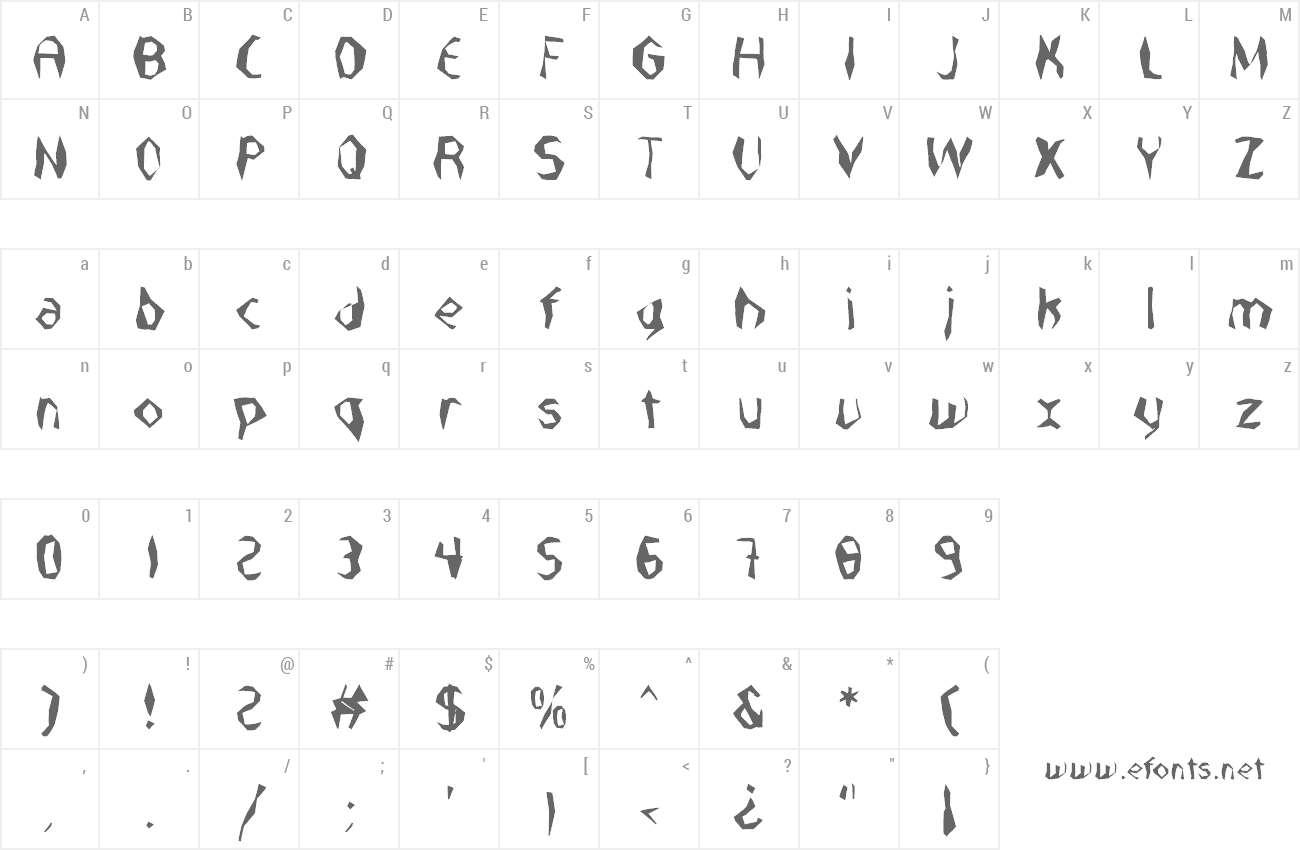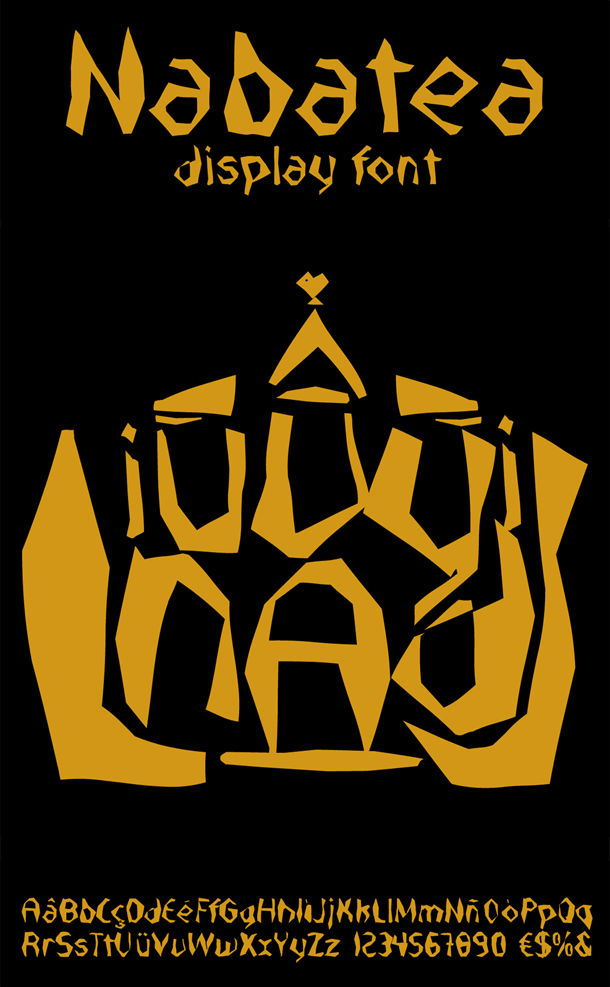
Preview and download Nabatea Font. Created by deFharo in Fancy Destroy styles with 100% Free license.
Nabatea es una letra hecha a colpe de mazo, sobre la dura piedra, por el individuo de un antiguo pueblo de la Arabia Pétrea, entre el mar Rojo y el río Éufrates. La tipografía es un homenaje a Petra, capital nabatea. Esta es una fuente con personalidad para usarla en Carteles y posters tipográficos, logos o títulos. Saludos. http://defharo.com/fonts/descargar-fuentes-gratis/ |